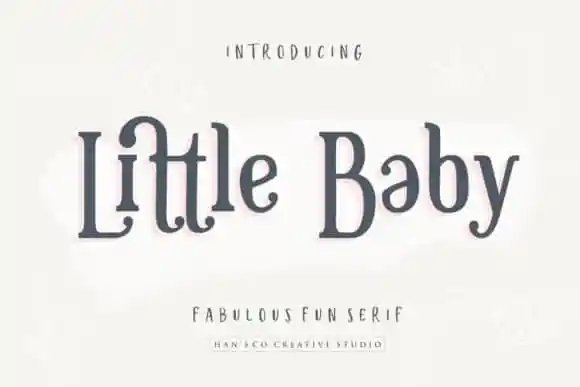
Little Baby Serif Font – Download Grátis
A Little Baby Serif Font é uma fonte muito versátil que oferece mais alternativas para caracteres e suporte a múltiplas línguas. Ela foi criada pelo designer HansCo, disponível na plataforma de desafios 99designs. Seu uso permite criar designs perfeitos em diversos tópicos como Design de Produto, T-Shirts, Cartões de Visita e Mercadoria, além de muitos outros. A Little Baby Serif Font também inclui o Modo Retrô que certamente dará um toque cool ao seu design. Este é um recurso atraente para designers buscando complementar suas criações com uma dose de nostalgia moderna. Perfect para aqueles que valorizam tanto versatilidade quanto estilo, essa fonte pode ser a escolha perfeita para tornar seus designs ainda mais atrativos e memoráveis.